제휴대폰에서 가끔씩 블로그를 검색해서 내용을 찾아볼 때가 있는데요 어떤 블로그는 글씨체가 굵고 선명해 보이고 어떤 블로그는 얇은 글씨체로 가독성이 떨어져 보일 때가 있습니다. 예전에는 그렇지가 않았는데 휴대폰 운영체계 One UI 6.0로 업데이트 한 후 얇게 보이니까 내용을 읽을 때 불편함이 있었는데요 간단하게폰트변경 방법으로 해결하는 방법을 정리해 보았으니 도움이 되었으면 합니다.
휴대폰 폰트 글꼴변경 방법
블로그 글자가 얇게 보이는분 주목~
휴대폰 글씨체를 한번 변경해 보고 싶으신 분~
5분 만에 간단하게 해결~
■ 휴대폰으로 블로그 볼 때 글씨가 얇게 보이는 현상
제가 휴대폰을 구매할 때 갤럭시 S22 울트라를 구입하였는데요 확실히 프리미엄 폰이라 기능 및 성능이 탁월하다고 느끼며 잘 사용을 해왔는데 운영체계를 One UI 6.0으로 업데이트한 후부터 가끔씩 블로그를 검색할 때 글씨체가 너무 얇아 가독성이 떨어지는 경우가 생기곤 합니다.
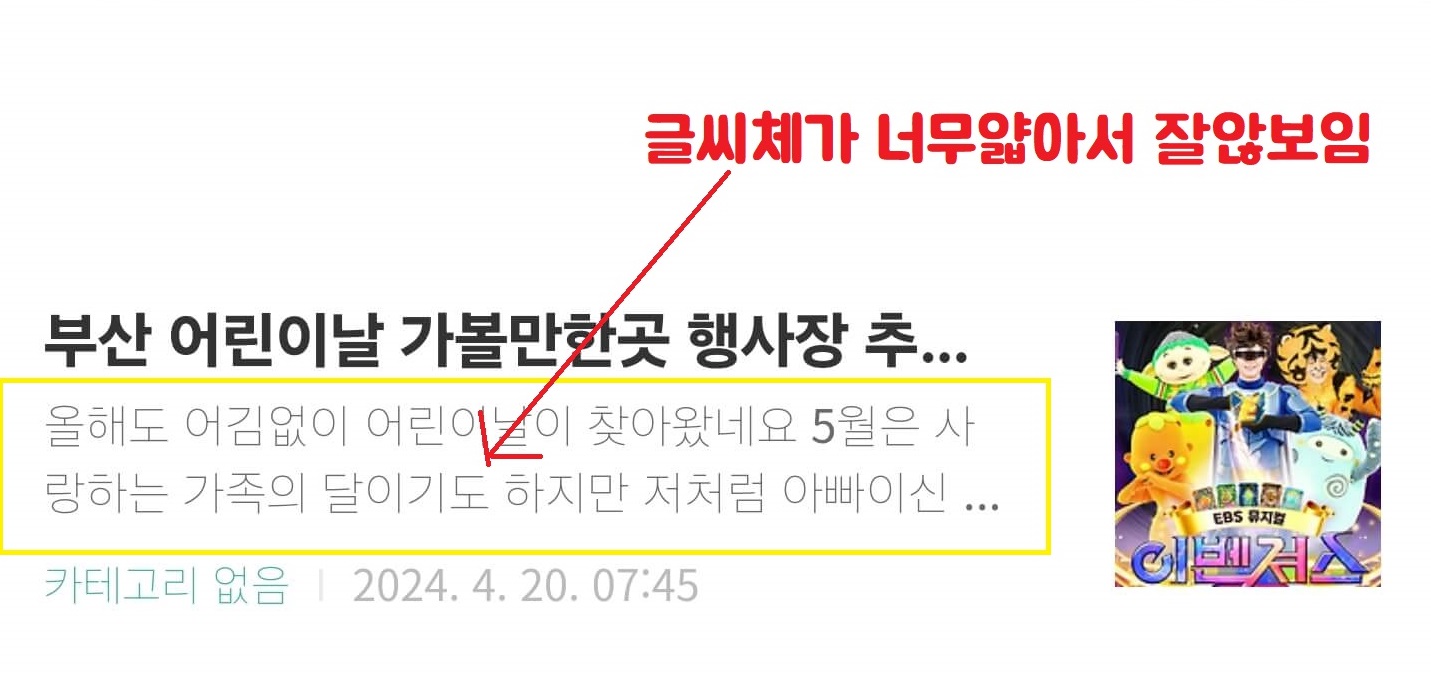
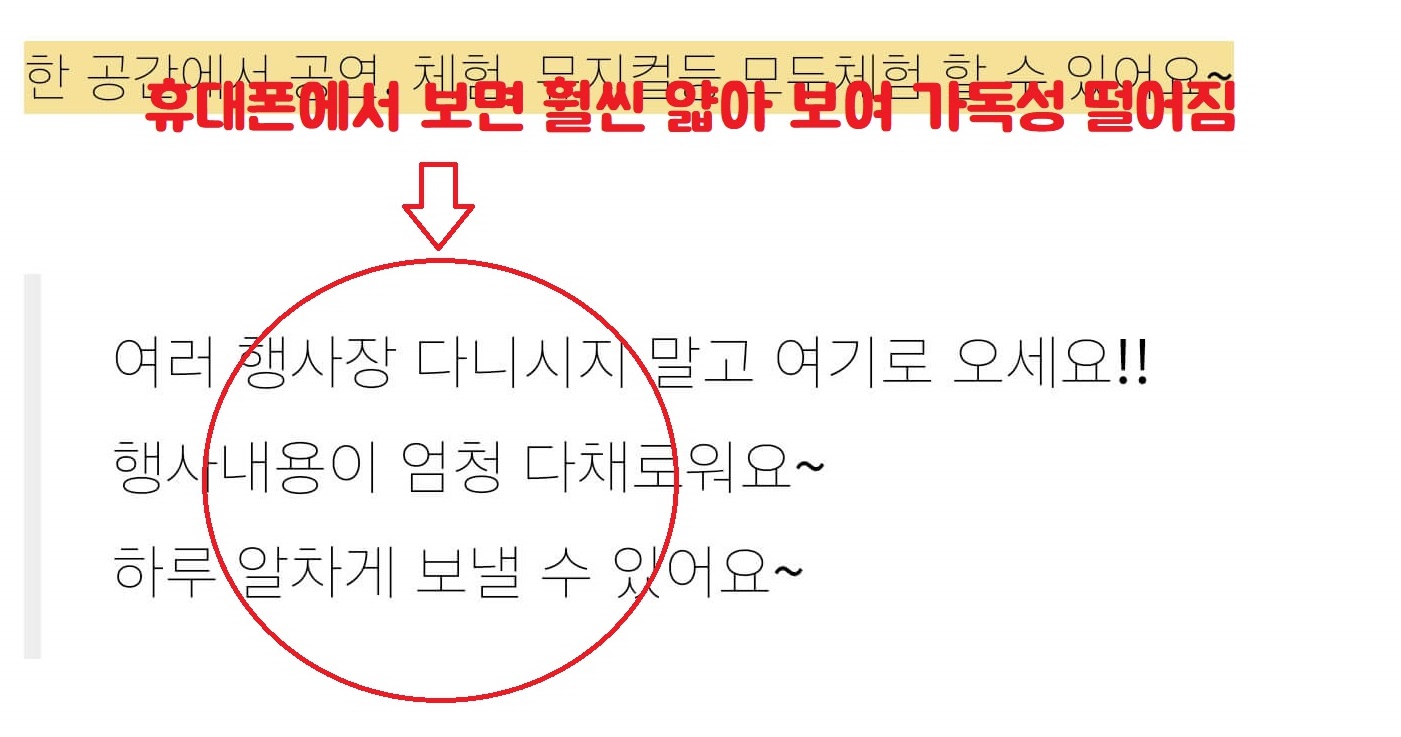
물론 블로그 자체의 폰트가 문제일 수가 있겠지만 내가 마음에 드는 블로그 내용을 볼 때 눈도 침침하고 잘 보이지 않는데 여간 불편한 게 아니더라고요 그래서 아들에게 물어봤더니 폰트변경하면 된다고 해서 5분 만에 폰트변경하고 가독성 좋게 사용하고 있으며 폰트종류도 아기자기한 폰트도 많으니 무료 또는 유로로 구매하셔서 휴대폰 분위기도 바꾸어 보는 것도 좋을듯하네요
폰트변경을 하는 방법은 정말 간단한데요 변경을 하고 나면 본인 휴대폰의 글자체는 전부 변경이 되게 됩니다. 예를 들어 기본글꼴이 바뀌게 되기 때문에 문자를 보낼 때의 폰트 그리고 바탕화면의 글씨체등 모든 폰트가 변경이 되고 인터넷 검색을 할 때 나오는 폰트 등 모든 폰트가 변경이 되기 때문에 마음에 들지 않으시면 다시 변경하면 되니 한번 사용해 보시는 것도 분위기 전환도 되고 괜찮을것 같습니다.
One UI 6.0 업데이트 후 블로그 폰트
저는 어떤 문제가 생기거나 확인해 볼일이 생기면 블로그 검색을 자주 하게 되는데요 운영체계 업데이트 전만 해도 모든 블로그의 글씨체가 일정하게 가독성 좋게 굵게 나왔는데 One UI 6.0 업데이트한 후 블로그 종류마다 글씨체가 굵게 보이는 것도 있고 얇게 보이는것도 있어서 은근히 불편하더라고요 원래 블로그 작성자의 폰트설정에 따라 그럴 수가 있겠지만 본인의 휴대폰에서 폰트변경만 하면 간단하게 해결을 할수가 있겠습니다.
휴대폰 폰트 글꼴 간단하게 변경하는 방법
간단하게 요약을 하자면 먼저 본인의 휴대폰 상단에 보시면 톱니바퀴 모양의 [설정]버튼이 있거든요 그 버튼을 누르시면 설정화면이 나오는데 돋보기 모양의 [검색]아이콘을 누르시면 글꼴변경 항목을 찾아서 들어갈 수가 있습니다.
검색창까지 가셨으면 [검색란]에 "글꼴"이라고 검색을 하시면 [글꼴]변경하는 항목으로 들어갈수가 있어요 그러면 [글자크기와 스타일] 창이 나오는데 글꼴을 보시면 기본으로 설정이 되어있을 것입니다. 그리고 글자 굵게 사용하는 체크항목과 글자크기를 조절할 수 있는 항목도 있는데 이 부분은 본인이 필요하신 만큼 조절을 하시면 됩니다.
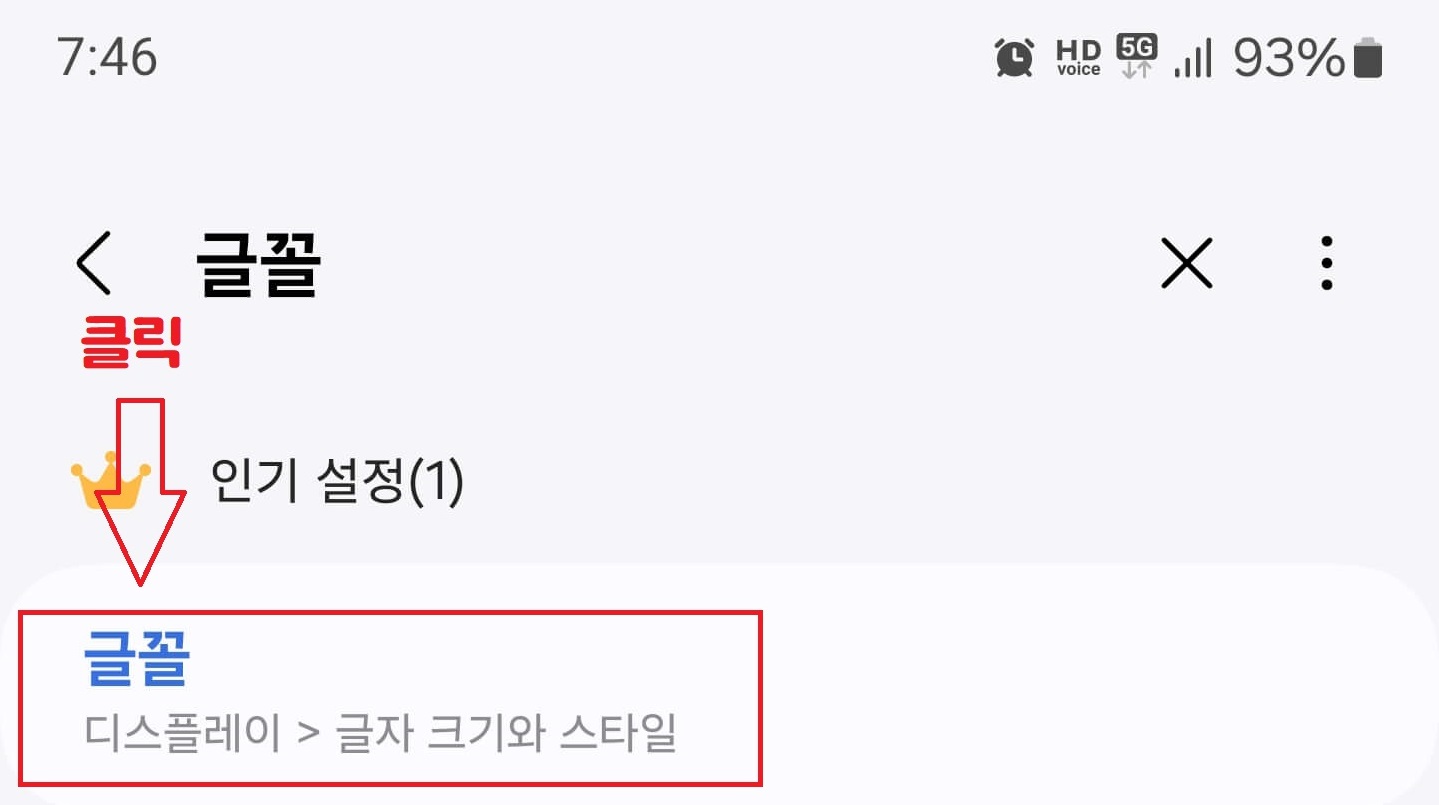
일단 [글꼴] 항목으로 들어가시면 내 휴대폰에서 사용할 수 있는 글꼴종류가 나오는데요 저는 여러 가지를 다운로드하여 마음에 드는 폰트를 사용하고 있는데요 중간에 보이는 [애플민트]는 너무 아이 같아서 사용하지 않고 문안한 폰트 SamsungOne 폰트를 체크하고 사용을 하니까 그냥 문안하고 보기 편한 것 같더라고요
만약 본인의 휴대폰에 원하는 글꼴이 없으시다면 맨 밑에 [+글꼴다운로드]에 들어가셔서 다운을 받으시면 되는데요 유료도 있고 무료도 있기 때문에 필요하신 데로 선택하셔서 다운로드하시면 될 것 같습니다. 원하시는 글꼴은 선택하셨으면 변경이 되었기 때문에 편리하게 사용하시면 되고요 혹시 마음에 들지 않는다면 다시 같은 방법으로 변경해서 사용하시면 되니 너무 어려워하지 마시고 시도해 보시길 바랍니다.
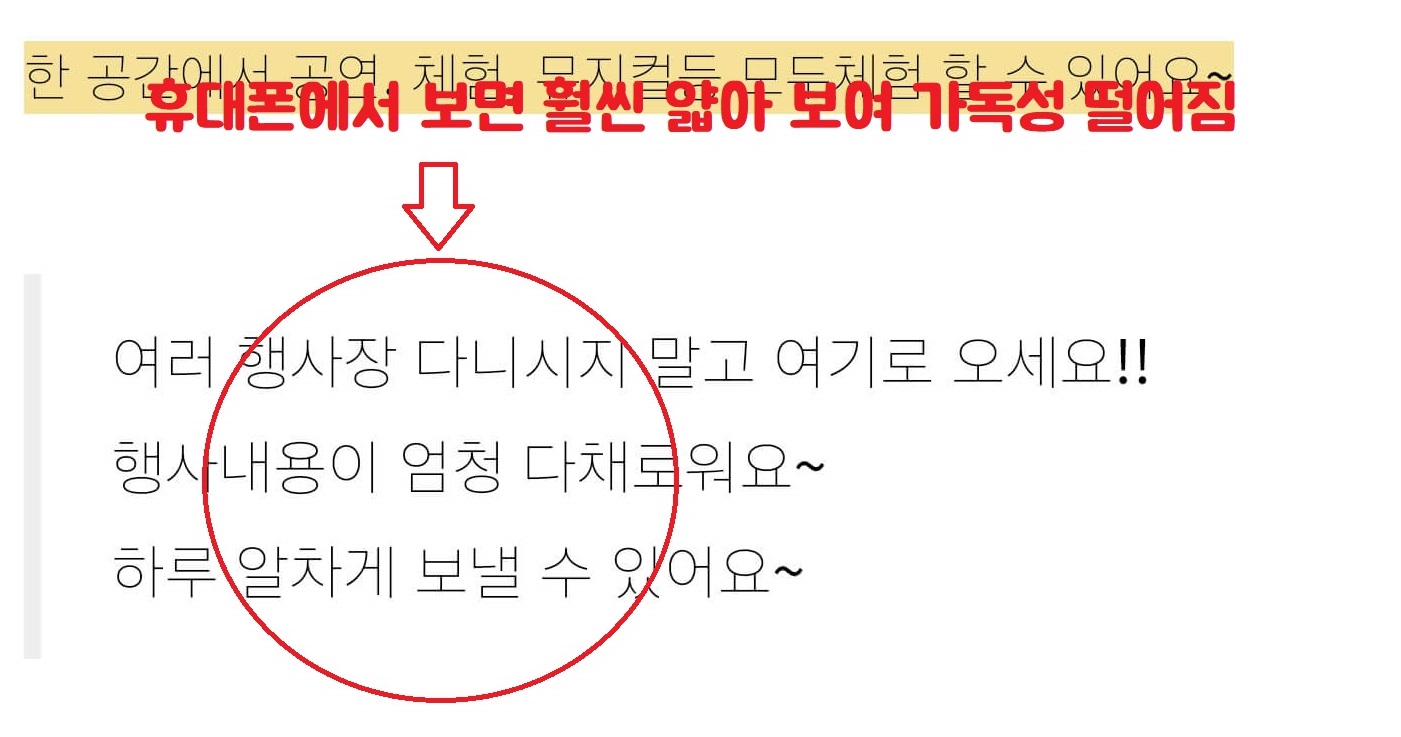
폰트변경이 끝나셨으면 본인의 휴대폰에 있는 모든 글자는 변경된 글자로 변경되어 표시가 되는데요 문자를 전송할 때 인터넷에서 나오는 글자들 모든 글자가 바뀌어지게 되고요 가끔씩 블로그 검색할 때 얇게 나오는 글자들도 굵게 선명하게 나오게 되니 확인해 보시면 될 것 같습니다. 만약 운영체게 One UI 6.0로 업데이트를 하지 않은 분은 상관없으시니 그냥 사용하셔도 되지만 기분전환으로 폰트변경을 하실 거면 사용하셔도 될 것 같네요
가끔씩 아무것도 아닌 것이 신경에 거슬릴 때가 있지 않나요 블로그가 마음에 들어 천천히 읽어보고 싶은데 눈도침침한데 글씨체까지 얇게 보이는 경우 다른 블로그를 또 검색을 해야 되니 소소하게 불편하더라고요 그래서 확인해 본 결과 간단하게 폰트만 변경하니 해결이 된다고 해서 잘 사용하고 있으니 참고가 되었으면 합니다.